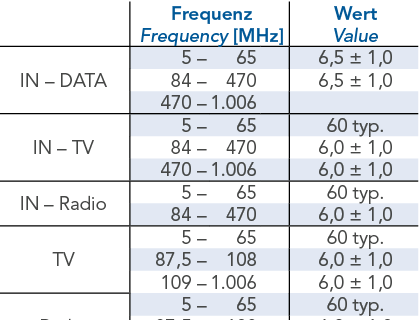
Anordnung von Zahlen mit "–" untereinander
Warum finde ich zu diesem Thema im Netz so wenig?
Mein Problem: Wie richte ich eine Zahlenreihe, bestehend aus jeweils zwei Zahlen, getrennt mit einem "–" (bis), untereinander aus?
Beide rechtsbündig? Die linke rechts- und die rechte linksbündig? Den Strich zentriert?
Zur Veranschaulichung anbei ein Screenshot.
Zentriert untereinander, so wie rechte Spalte.
Zur Tabelle: die horizontalen Einfärbungen der Zeilen finde ich störend, denn je nach Anzahl (ungerade, gerade) ergibt sich für das Auge ein Muster (Wechsel hell-dunkel), das den schwarzen Zellbegrenzungen zu widerläuft.
Und den Gedankenstrich benutzen. Im obigen Bild liegt der Strich merkwürdig tief und vermittelt so nicht auf Anhieb das Lesegefühl »von – bis«.
Das ist ein Gedankenstrich. Ist auch bei Satz mit Groß- und Kleinbuchstaben passend. Bei Ziffern oder Versalsatz sieht er zu niedrigstehend aus.
Es gibt aber bei den meisten Schriften eine Versalform des Gedankenstrichs. Diese steht höher als der üblich verwendete Gedankenstrich.
Wenn du über die OpenType-Funktion „Großbuchstaben“ anklickst, wird der Gedankenstrich automatisch höhergestellt.
Schwierig mit der Zweisprachigkeit. Im Englischen stehen Punkte statt Komma bei der Dezimaltrennung. Sprich, sie würden die Werte falsch lesen.
Zweisprachigkeit
Ja, ich würde auch die Tausenderpunkte weglassen, ich hab ja jetzt schon 1,006 MHz gelesen ...
Und wie könnte man die Kommata bei den Werten elegant zweisprachig machen?
Hach, da bietet doch der Zeichensatz eine Lösung: 6;5
Mit 1000er Trennzeichen dann 1⸵006;5
... bei richtiger vertikaler Anordnung der Sprachen, sonst eben umgekehrt ...
Also ernsthaft wüsste ich da außer 6½ nix ...
elegant zweisprachig
Oft schließt das eine das andere aus ;) Für so etwas gibt es glücklicherweise Standards wie SI oder ISO 80000, die nun nicht eindeutig sind, weil sie den sprachlichen Gewohnheiten etwas Raum bieten. Jedoch verstehe ich die so, dass im Zweifelsfall -- wie hier -- dem Komma der Vorzug gegeben werden sollte.